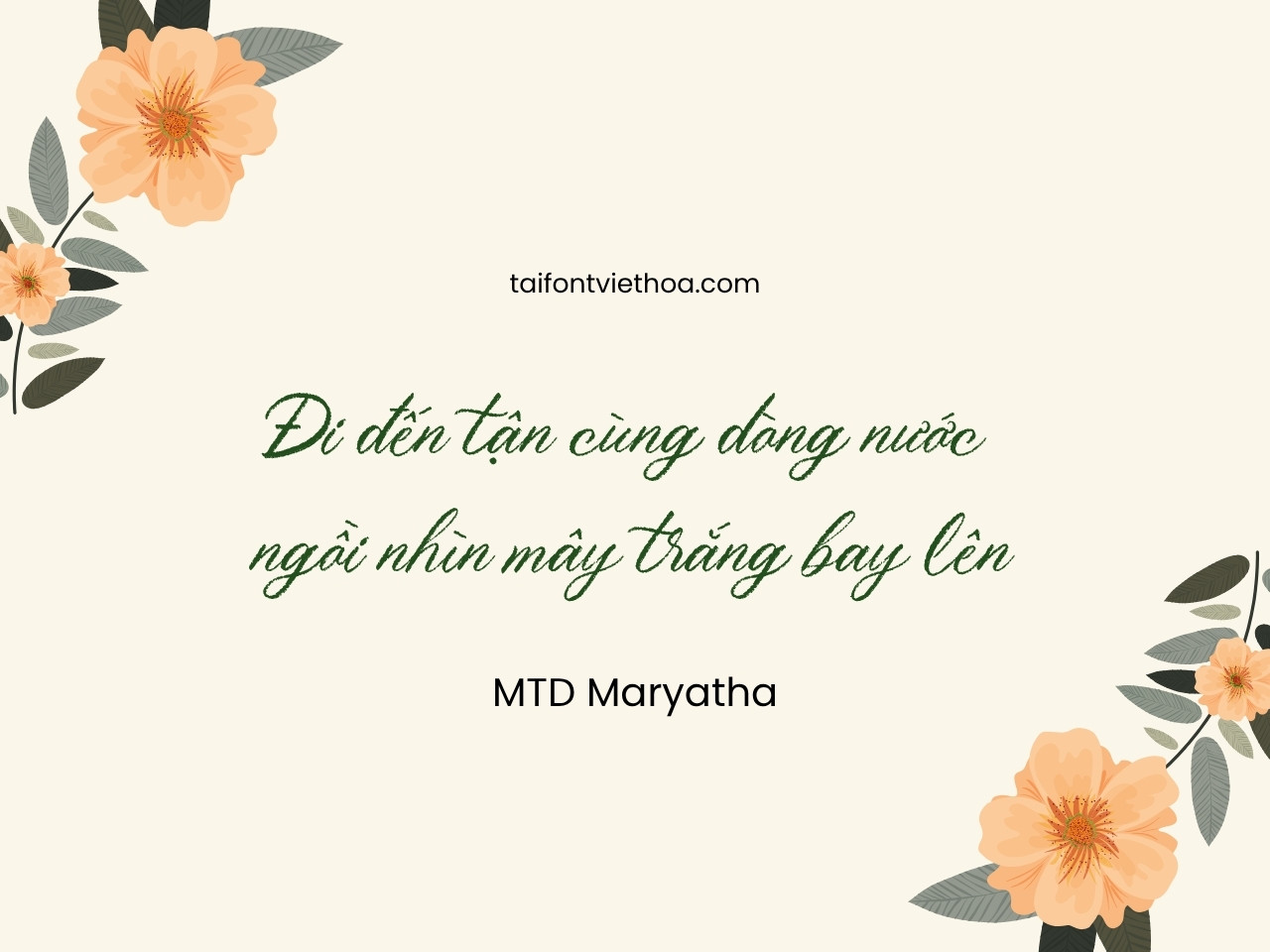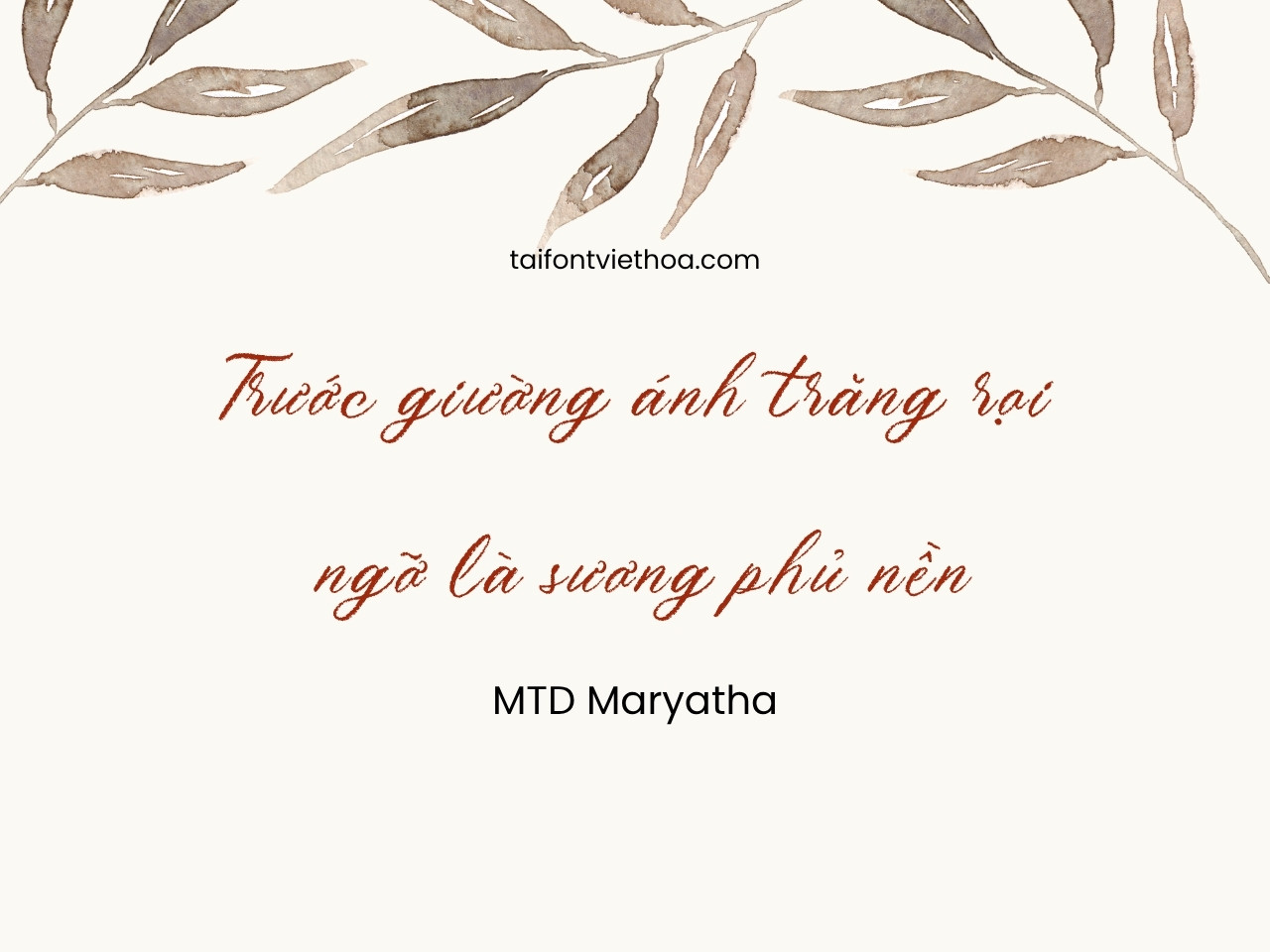
Font việt hóa MTD Maryatha
Tác giả Font: Ryan Prasetya
Giới thiệu về font Maryatha
Maryatha là một font script viết tay thanh lịch và duyên dáng do Motokiwo Type (MTD) thiết kế. Font mang phong cách nữ tính, nhẹ nhàng với các đường cong mềm mại, rất phù hợp cho các thiết kế cần sự tinh tế và cảm xúc như thiệp cưới, lời mời, hay logo cá nhân. Font Maryatha gợi nhớ đến những nét chữ viết tay mượt mà, có chiều sâu nghệ thuật nhưng vẫn đảm bảo độ dễ đọc và hài hòa thị giác. Phiên bản Việt hóa được chính MTD thực hiện, hỗ trợ đầy đủ dấu tiếng Việt và hơn 70 ngôn ngữ khác, giúp người dùng thoải mái sử dụng trong các dự án quốc tế và đa nền tảng.
Đặc điểm thiết kế và ứng dụng của font Maryatha
Maryatha được thiết kế với các ký tự nối liền tự nhiên, ligatures và swashes phong phú giúp tạo ra những dòng chữ giàu biểu cảm. Độ nghiêng nhẹ kết hợp với độ cong tròn hài hòa giúp font vừa có cảm giác bay bổng vừa giữ được trật tự trong thị giác. Đặc biệt phù hợp với các thiết kế cần sự thanh lịch và nữ tính.
Font Maryatha lý tưởng cho các ứng dụng như: thiệp mời, typography cảm xúc, bìa sách lãng mạn, logo spa, blog cá nhân, hoặc bao bì sản phẩm thủ công. Ngành nghề phù hợp gồm: cưới hỏi, thời trang nữ, mỹ phẩm, quà tặng handmade, thiết kế cá nhân hóa, và các chiến dịch quảng cáo hướng đến cảm xúc và nữ giới.